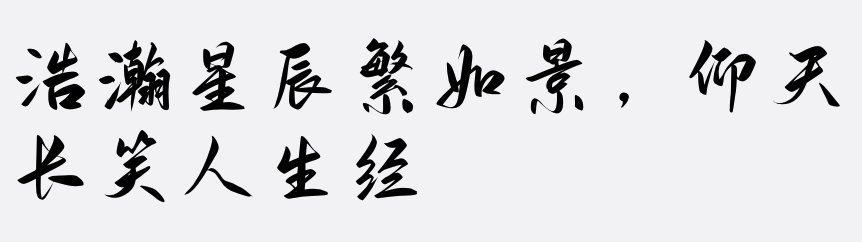
古风字体风格多样时而气势磅礴,时而飘逸灵动,适合一些古典风格的网页,比如诗词的书写,亦可以运用在海报广告设计当中。今天分享的这款醉清风字体,喜欢的可前往字体视界官网搜索下载。
醉清风介于行书和草书之间。偏于草书但字形尽量保持行书识别标准,方便现代非专业人士认知和识别,注重实用功能。快书承袭逸龙体既有的飘逸洒脱,行云流水,矫若游龙。
醉清风